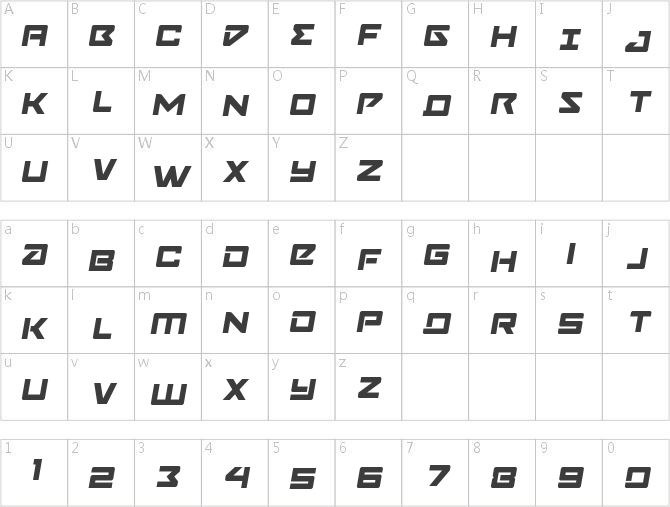
Navy Cadet Semi-Italic
Navy Cadet Semi-Italic介紹
Navy Cadet Semi-Italic字體字庫是一款讓人賞心悅目、百看不厭的英文字體,適合各類廣告和產品包裝設計應用,字體大小0.03MB,格式為ttf字體,上傳用戶是東方時尚,作者/版權方為未知